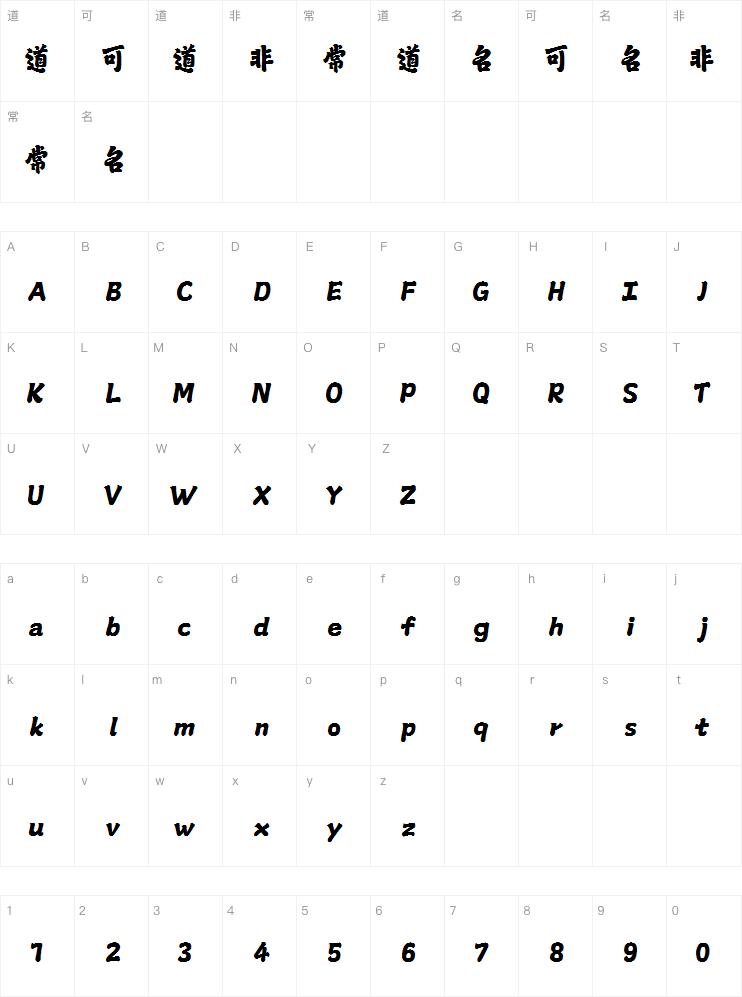
山海狂想曲w
山海狂想曲,是一款全新的字体,包含汉字9169个,符号200+个。该字体是一款卡通风书法字体,该字体字形灵动多变,童趣可爱,同时融入手写风笔势,各种连笔笔画,整体笔触圆润,活泼清新,造型生动有趣,具有灵活的适用性,天真俏皮又不失时尚感。该字体字形随手写习惯大小不一,各个字的大小随字形的不同而呈现不同的大小,但是在变化中寻求平衡,在多变的同时有保持整体均衡匀称,使得整个字体更具有手写感的温度和节奏感,整体笔触圆润,灵动笔画贯穿笔画始终,同时融入行书书法元素,内涵丰富,弧度柔和,撇笔平缓舒展,尽显俏皮灵动。